Seguimos con los ejercicios de lettering que os traigo en este blog y en mi canal de Youtube Azahara Letras – Caligrafía y Lettering. Hace tiempo que tenía ganas de dedicarle un artículo y un vídeo a un tipo de lettering que me gusta mucho, es el que se llama lettering de lazos, letras lazo o ribbon letters. Su nombre se debe a que con unos trucos de dibujo se consigue que las letras parezcan un lazo que crea bucles y que se estira, creando efectos de curvas y de volúmenes. En la siguiente imagen trato de realizar una «e» con una cinta de raso para que veáis a qué me estoy refiriendo:
Materiales necesarios
Para realizar este hand-lettering de letras lazo necesitáis un rotulador de punta flexible o punta de pincel de dos colores que estén cerca de la gama cromática (por ejemplo, azul claro y azul oscuro), un bolígrafo de punta fina o gruesa y un cuaderno satinado que no estropee la punta de los pinceles. Yo he utilizado estos materiales concretamente:
Recordad que si no tenéis estos materiales, no pasa nada. Podéis hacer falsa caligrafía con cualquier rotulador de punta normal que tengáis en casa y sustituir el puntafina por un bolígrafo negro o azul oscuro.
Ejercicio para dibujar lettering de lazos o ribbon letters
Ahora que sabemos qué efecto queremos crear y los materiales necesarios para conseguirlo, vamos con el tutorial paso a paso.
Paso 1
El primer paso es escribir el alfabeto con un rotulador de punta flexible o punta de pincel con un tipo de caligrafía Script, trazos finos hacia arriba y trazos gruesos hacia abajo. Es lo que algunos llaman Brush Lettering. Eso ya os lo enseñé en este artículo, así que no voy a incidir en ello.
Paso 2
El segundo paso se puede realizar de dos maneras, una es perfilar todo el contorno de cada letra, es decir, delinear la silueta utilizando el bolígrafo de punta fina, tal y como veis en la imagen superior.
Paso 2 (alternativa)
La otra manera del realizar el paso 2 es no delinear la letra de momento, tomar el rotulador del color más oscuro y repasar los trazos finos de cada letra, como yo he hecho con la letra «b». Otra manera es pintar solo el inicio del trazo fino y el final y degradar el resto.
Con este toque tan sencillo, ya se consigue un poco el efecto de lazo, pero lo vamos a potenciar con otro truco.
Paso 3
Siguiendo la primera manera de hacer el paso 2, después de delinear toda la letra, llega la parte que para mí es la más complicada, y es la de delinear los trazos para crear este efecto de giro, decidiendo qué trazo va por arriba y qué trazo va por abajo. Por ejemplo, una posibilidad a la hora de dibujar la «a», sería esta:
Paso 3 (alternativa)
Si hemos optado por la alternativa de pintar los trazos finos primero, entonces, el siguiente paso es delinear con el bolígrafo de punta fina los trazos que quedan en sombra, que pueden ir por arriba o por abajo, como hago con esta letra «b»:
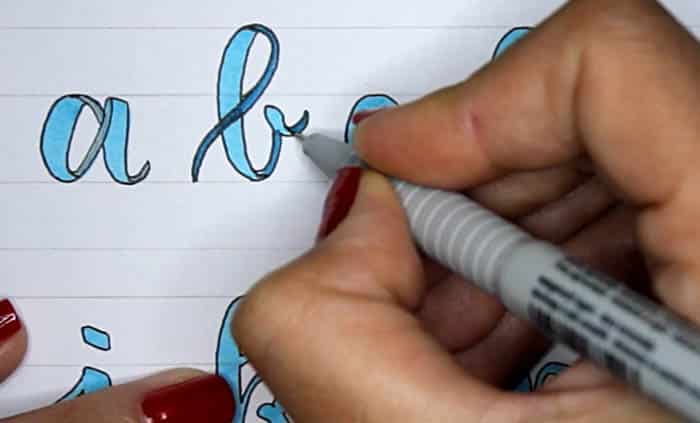
Paso 4
El siguiente paso es hacer las sombras en los trazos finos que ya hemos delineado, ya sea sombreando con un lápiz o un color gris o con el rotulador más oscuro directamente.
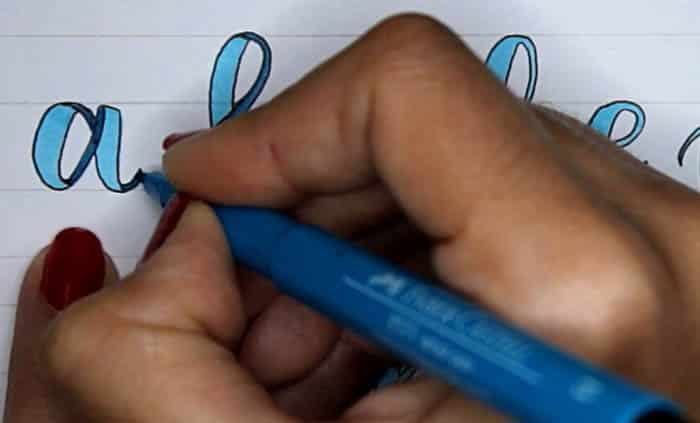
Paso 5
Cuando entendáis esta dinámica, que ya os aviso que no es fácil, entonces tenéis que hacer lo mismo con las otras letras.
Es bastante difícil de explicar por escrito y de que lo veáis, por eso os recomiendo que le echéis un vistazo al siguiente vídeo en el que os explico cómo dibujar todas las letras lazo del alfabeto paso a paso.
Vídeo cómo dibujar unas letras lazo
Lo dicho, es una técnica bastante difícil de realizar si no se tienen conocimientos de dibujo en cuanto a volúmenes y sombras, por eso os recomiendo ver este vídeo de mi canal Azahara Letras (¡suscribíos, por favor!) en donde lo podréis ver todo con detalle y en donde os lo explico estupendamente 🙂